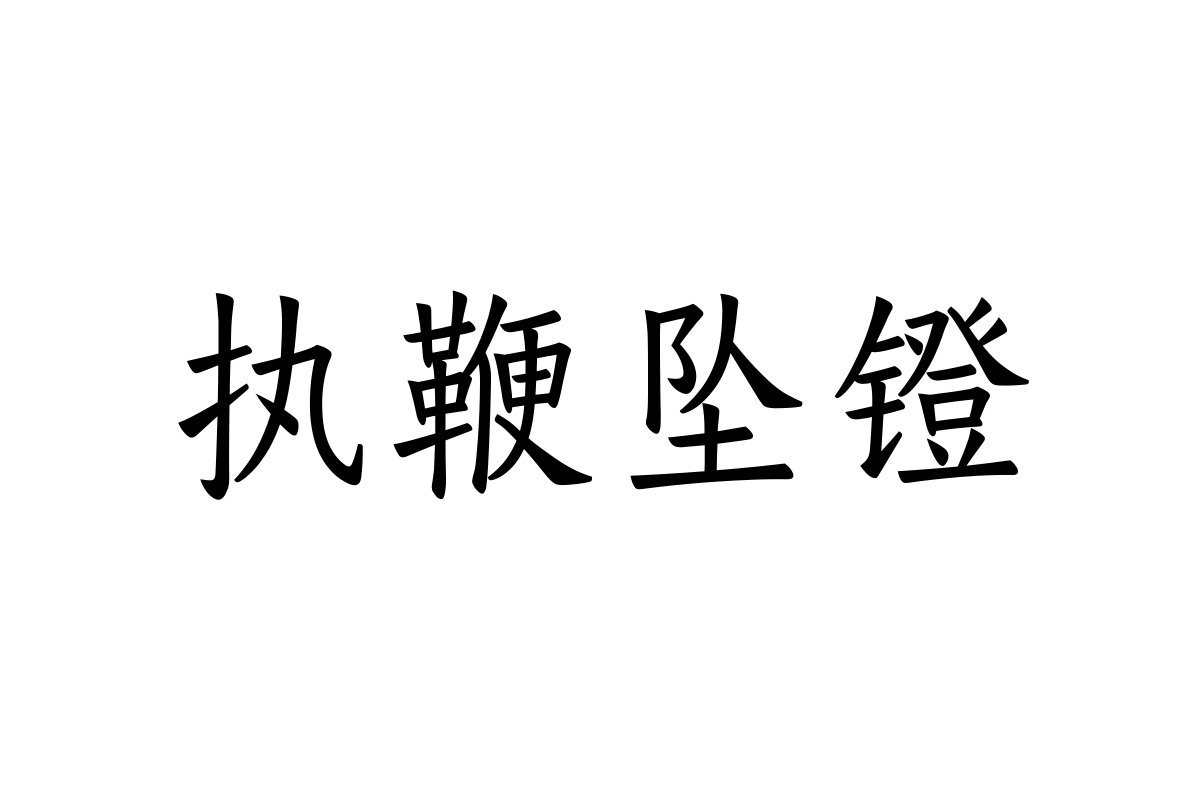
汉仪楷体45是一款具有独特风格和特色的中文字体。它以其简洁、清晰的特点,深受广大用户的喜爱。这款字体采用了传统的书法笔触和结构,使得每个字都显得饱满而有力。同时,它的笔画粗细适中,既不过于纤细也不过于粗壮,给人一种平衡而舒适的感觉。
汉仪楷体45的字形结构紧凑,线条流畅,无论是在印刷品还是电子屏幕上都能展现出良好的视觉效果。它的适用范围广泛,包括标题、正文、广告等各类文本内容。无论是商业宣传、教育学习还是个人创作,汉仪楷体45都能成为您的最佳选择。
总之,汉仪楷体45是一款非常实用的中文字体。它的简约风格和独特韵味,使得它在众多字体中脱颖而出,成为了众多设计师和用户的心头好。无论是用于品牌标识、产品包装还是网页设计,汉仪楷体45都能为您的作品增添一份独特的魅力。